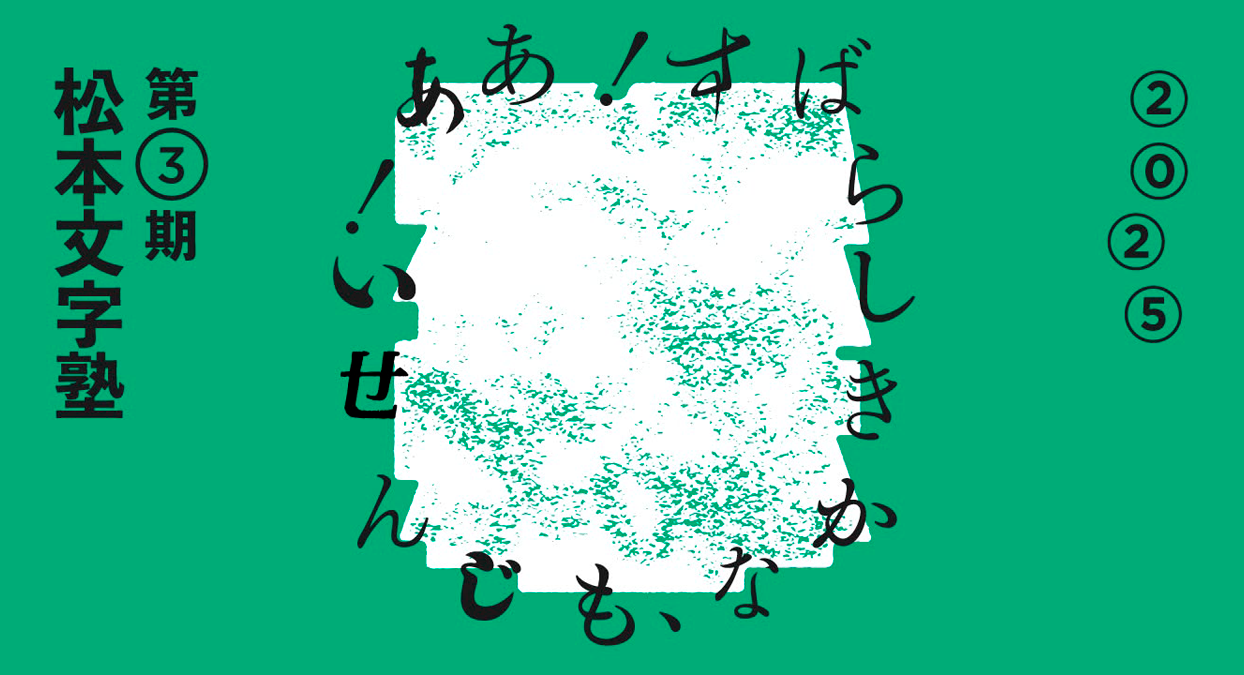
一年をかけて自分の仮名(平仮名、片仮名)を作り、フォント化して、その成果を展示会で発表するという塾です。
日本語フォントを作ろうとすると、漢字・平仮名・片仮名・アルファベット・記号など、最低でも約1万字を制作しなければなりません。一年という期間の中で、個人で実現するのは不可能と思われるので、この塾では平仮名・片仮名にしぼって制作します。
日本語表記において、平仮名・片仮名が約6割以上を占めるなど、新しい仮名を利用することで、まったく新しい組版イメージを得ることができます。そのうえ日本で生まれたわが国固有の文字である仮名について学ぶことはとても意味のあることだと思います。
今期文字塾でも、例年どおり手で書くことを前提としながら、明朝体の仮名を作ることを基本に指導をしていきます。ただし明朝体以外の仮名書体に挑戦したいという希望があれば、可能な限りサポートはします。
文字塾では自分の仮名書体を作るだけにとどまらず、文字そのものの歴史や活字の歴史、活字の構造、書体デザインの考え方などにも踏み込んでレクチャーします。その中から良いデザインとは、自分らしい書体とはどういうものなのかを探り出せたら良いと思います。私はそのお手伝いをする立場です。初心者・プロを問いませんが、一年間、自分の感覚と真摯に向き合い、自分の文字を探求する粘り強さを期待します。
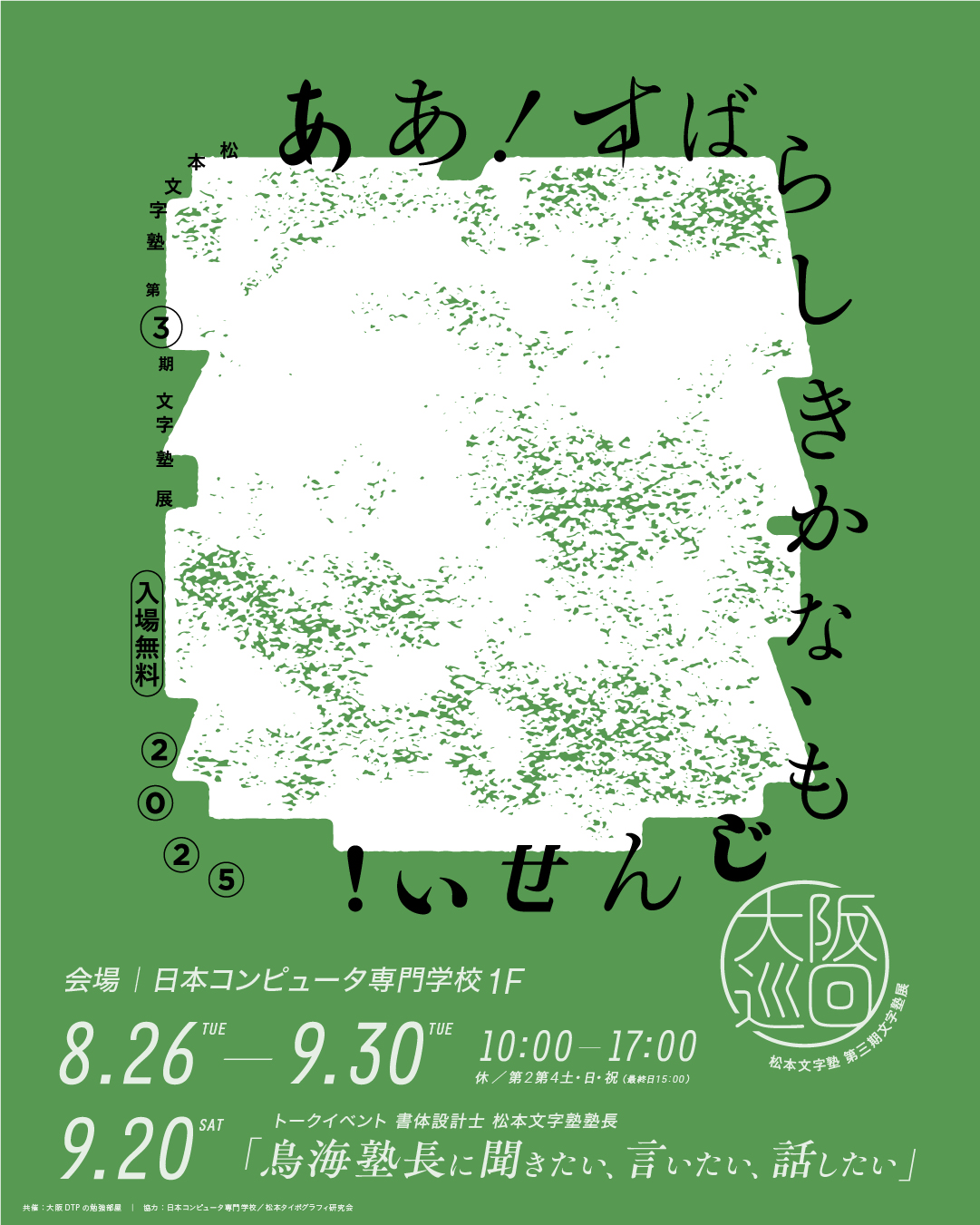
松本文字塾 第三期 文字塾展「ああ! すばらしきかな、もじんせい!」|大阪巡回
◉松本文字塾 第三期 文字塾展 大阪巡回
◉鳥海修 文字塾塾長トークイベント
「鳥海塾長に聞きたい、言いたい、話したい」
松本文字塾 第三期 文字塾展「ああ! すばらしきかな、もじんせい!」
文字塾は、塾生が1年をかけて各人の仮名をデザインする私塾です。2012年から8年間にわたり東京で続けた文字塾は、2022年4月に信州松本に拠点を移して「松本文字塾」として再スタートしました。
今回の展示は2024年度の第3期松本文字塾生、総勢14名によるものです。学生、グラフィック、Web、DTPの各デザイナー、新聞社のデザイナー、ウタウタイ、プロの書体デザイナーなど職業もばらばらで、年齢層も20代前半から50代まで、東京、大阪、兵庫、福井、長野、さらに台湾からも参加し、幅広い方たちが集いました。
文字塾では各自が定めたコンセプトのもと、1年間自分の文字と向き合います。原則は明朝体なのですが、さまざまな事情でそうでない書体もあります。しかしどちらにしても手で書き、迷い、修整を繰り返した結果が今回展示した作品です。うまくいったものもそうでないものも、いずれにしても発展途上のものです。仮名書体を作ることは楽しいのですが、なかなか思うように行きません。比較的思うように作れるようになるまでには、経験上10年はかかると思います。
そんな発展途上の作品ですから厳しくも暖かく見守っていただけたら幸いです。またその過程をまとめたファイルは作品以上に貴重な記録だと思います。合わせてゆっくりとご覧ください。
一年をかけて自分の仮名(平仮名、片仮名)をつくり、フォント化して、その成果を展示会で発表するという塾です。
日本語フォントを作ろうとすると、漢字・平仮名・片仮名・アルファベット・記号など、最低でも約1万字を制作しなければなりません。一年という期間の中で、個人で実現するのは不可能と思われるので、この塾では平仮名・片仮名にしぼって制作します。
日本語表記において、平仮名・片仮名が約6割以上を占めるなど、新しい仮名を利用することで、まったく新しい組版イメージを得ることができます。そのうえ日本で生まれたわが国固有の文字である仮名について学ぶことはとても意味のあることだと思います。
今期文字塾でも、例年どおり手で書くことを前提としながら、明朝体の仮名を作ることを基本に指導をしていきます。ただし明朝体以外の仮名書体に挑戦したいという希望があれば、可能な限りサポートはします。
文字塾では自分の仮名書体を作るだけにとどまらず、文字そのものの歴史や活字の歴史、活字の構造、書体デザインの考え方などにも踏み込んでレクチャーします。その中から良いデザインとは、自分らしい書体とはどういうものなのかを探り出せたら良いと思います。私はそのお手伝いをする立場です。初心者・プロを問いませんが、一年間、自分の感覚と真摯に向き合い、自分の文字を探求する粘り強さを期待します。
12人の想いが宿った個性溢れる書体の表情をぜひお楽しみください。